Новейшие шрифты за 2015 год для Ваших проектов совершенно бесплатно
Друзья, это свежайшая подборка самых новых и очень стильных шрифтов. Они подойдут практически для каждой цели, как для сайтов, так и для различных типографических изданий и журналов. Ну и конечно же все шрифты совершенно бесплатны.
Бесплатный шрифт из нескольких частей — SLOT
Необычный и жирный шрифт для сайта — LAURA
Шрифт в дырку под названием — PERFOGRAMA
Тонкий шрифт в несколько линий — TRITIO
Шрифт от руки — REFUGE
Жирный и бесплатный шрифт на Ваш сайт — RANCHO
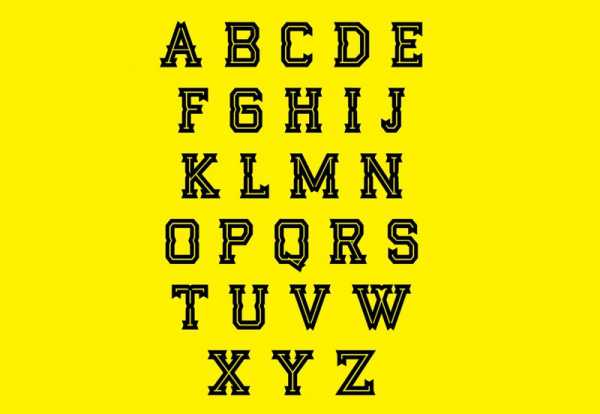
Минималистический шрифт с жирным начертанием — GEOMANIST
Отличный шрифт с различным начертанием — BEBAS-TAM
Шрифт в арабском стиле — MODAK
Декоративный шрифт — ALLEGHENY
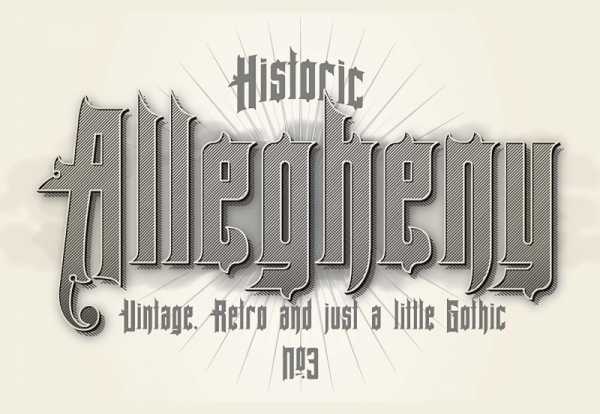
Необычный шрифт для использования на Вашем сайте — ORDNUNG
Крутой и двойной шрифт — TIMBER
Тонки шрифт с интересным начертанием — GOGÓIA
Простой шрифт с жирным начертанием — NURJAN
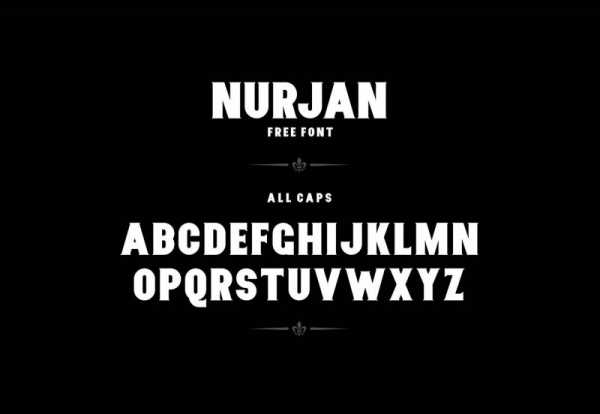
Отличный шрифт для творческого сайта — PONIENTE
Немного растянутый шрифт — VELODROMA
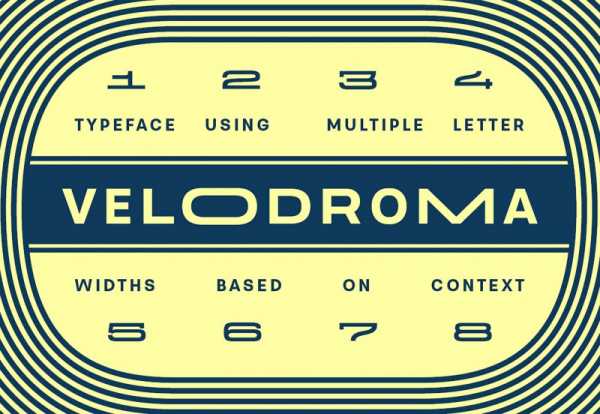
Шрифт написанный от руки — HAND-CRAFTED
Шрифт для фото сайтов — PIER
KANEDA — декоративный шрифт на сайт
Обычный и простой шрифт бесплатно — AILERON
Необычный шрифт с острыми углами — OHMEGA SANS
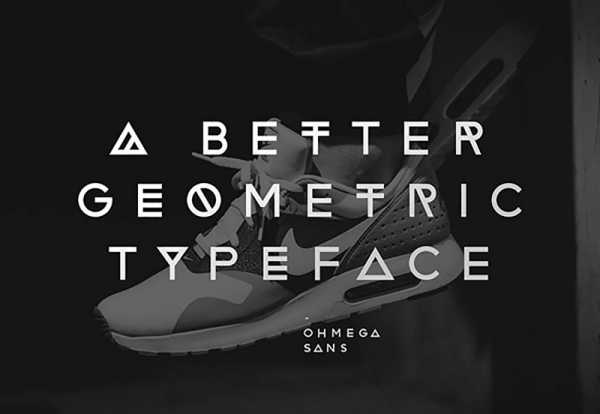
Крутейший шрифт с простым названием — AO
Двойной и жирный шрифт — KANJI
Шрифт написанный кистью — BELLABOO
Шрифт от руки — STREAMSTER
Творческий шрифт для сайта — RUNAWAY
Простой шрифт от руки для Вашего сайта — BASULTO
Необычный шрифт с тонкими линиями — BARCELONA
Минималистический шрифт на сайт — MANUFRAKTUR
Необычный и декоративный шрифт будущего — QG
Шрифт в стиле Долларовой банкноты — DOLLAR BILL
Шрифт с шумом — MAXWELL
Шрифт в стиле вестерна — WESTERN GRIT
Шрифт с тонкими линиями но с жирным начертанием — TRESDIAS
Простой и светлый шрифт для фото сайта — WHITE PINE
Ещё один шрифт будущего — NORDIC
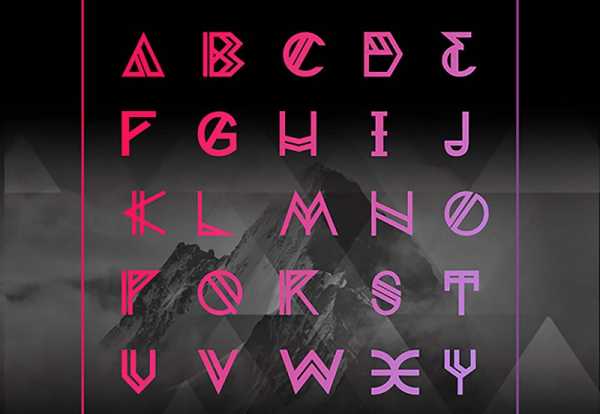
Шрифт написанный от руки толстой кистью — GALLOW TREE
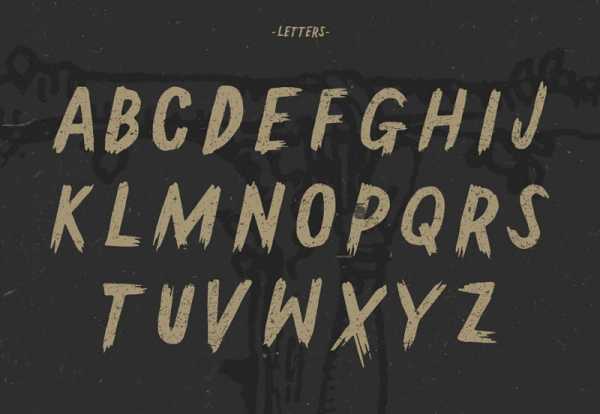
Туристический шрифт — YAPA
Декоративный шрифт — GROWL